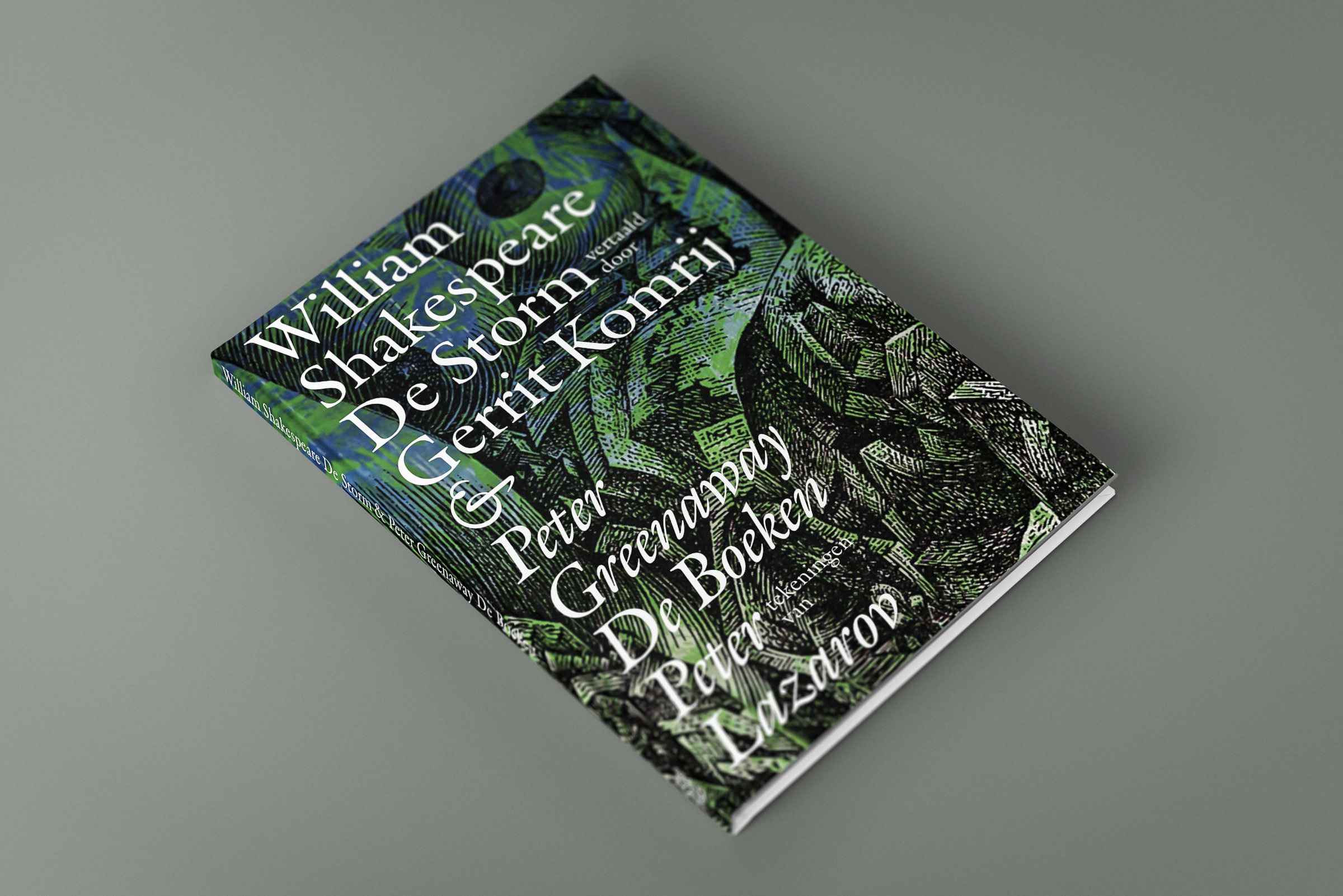
Cover-Studien
Die Schriftart Romaine im fiktiven Einsatz auf verschiedenen Buchcovern
Weil Aad van Dommelen sehen wollte, ob seine Romaine wirklich so gut im Buch- und Editorial-Design funktioniert wie geplant, probierte er sie anhand einiger fiktiver Projekte aus. Aus diesen Studien sind hier Buch- und Magazin-Cover zu sehen.
Die Schriftart Romaine im fiktiven Einsatz auf verschiedenen Buchcovern